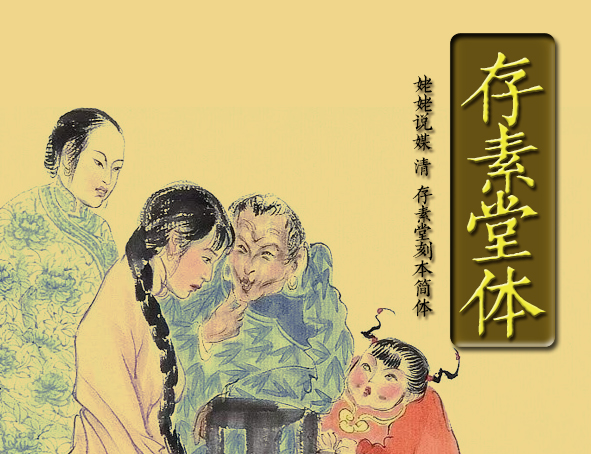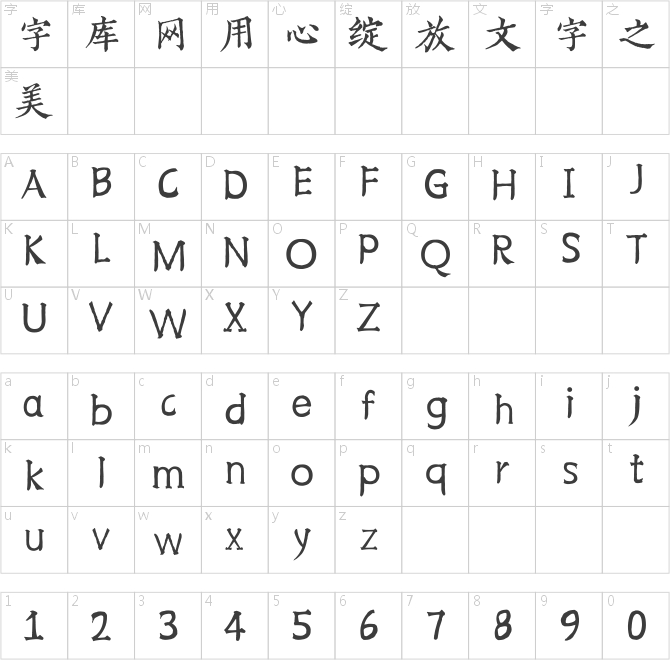
姥姥說(shuō)媒(清)存素堂刻本簡(jiǎn)體 詳情頁(yè)
姥姥說(shuō)媒(清)
姥姥說(shuō)媒(清)存素堂刻本簡(jiǎn)體字體下載存素堂刻本簡(jiǎn)體
姥姥說(shuō)媒(清)存素堂刻本簡(jiǎn)體,字體以采用中華古籍書《存素堂文集》清嘉慶時(shí)期揚(yáng)州程邦瑞刊本為藍(lán)本,該字體屬于內(nèi)文排版范疇,其書風(fēng)收放自如、筆力蒼勁、雄偉開拓,適用于書籍的封面,以及品牌廣告和產(chǎn)品包裝設(shè)計(jì),尤其適合做古籍內(nèi)文用字。
姥姥說(shuō)媒(清)存素堂刻本簡(jiǎn)體字體存素堂刻本簡(jiǎn)體字庫(kù)是一款讓人賞心悅目、百看不厭的中文字體,適合各類廣告和產(chǎn)品包裝設(shè)計(jì)應(yīng)用,字體大小6.16MB,格式為ttf字體,上傳用戶是邯鄲字庫(kù),作者/版權(quán)方為韓紹杰